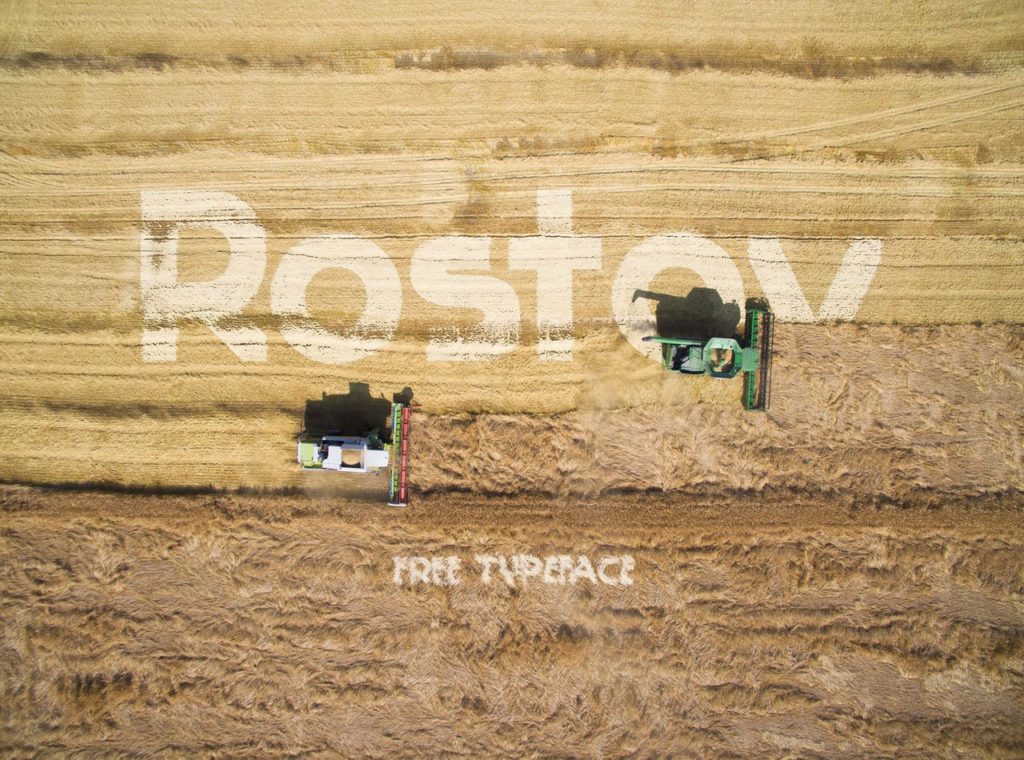
Шрифт Rostov — это современный кириллический гротеск от российского дизайнера Андрея Усикова (2017 год). В основе начертания лежит строгая геометрия и классическая конструкция без засечек, что делает его универсальным инструментом для оформления заголовков. Шрифт обладает выразительными деталями, характерными для авторских дисплеев, при этом сохраняет высокую читаемость. Отлично подходит для создания логотипов, айдентики и веб-дизайна в современном стиле. Скачать кириллическую версию бесплатно можно по ссылке ниже.